Début septembre, j’ai eu la chance d’être choisie comme sujet pour un travail photographique. Le thème de ce travail était « Art & Matière », et il fallait que la photographe suive le process d’un artiste sur une journée. J’ai proposé non pas de mettre en scène un sujet sur la calligraphie elle-même, mais sur la réalisation d’encrages de végétaux. D’une part, je trouvais le sujet plutôt photogénique, d’autre part, j’avais envie de faire quelques encrages avant la fin de l’été.
Emmanuelle, photographe amateur en cours de formation à l’institut Nicéphore, est donc venue me retrouver dans ma campagne pour shooter la séance de A à Z. Elle a décrit son travail sous l’angle photographique dans un bel article reprenant ses clichés en noir & blanc (contrainte imposée pour son devoir). Je vous livre ici ma version des faits, illustrée par ses très belles photos, en couleur cette fois-ci.
Les élèves de Marine Porte de Sainte-Marie qui suivent Lettres & Co reconnaîtront une technique qu’elle a mise en scène dans de nombreuses œuvres, comme celles illustrant l’article sur la composition. C’est en effet dans son atelier que j’ai appris à réaliser des encrages, en 2015. C’est un stage qu’elle propose chaque année et qui remporte un immense succès, amplement justifié.
Si vous passez par ici et que vous avez prévu d’aller faire son prochain stage d’été, pas de souci, l’article n’est pas un SPOILER ! J’explique simplement quelques étapes de travail, et vous laisse le plaisir de découvrir l’intégralité de cette technique étonnante lors de votre stage !
A la recherche de végétaux
Au point de départ, il y a bien sûr la recherche de feuillages, d’herbes et de fleurs. En forêt, dans votre jardin, en bordure des champs, il faut se laisser porter et sélectionner une belle variété de végétaux. C’est l’occasion d’une jolie ballade-cueillette, avec un petit panier en osier. L’occasion aussi de porter son attention sur toutes ces herbes qui bordent les chemins et auxquelles nous ne faisons pas forcément attention, alors qu’elle ont des formes très graphiques ou très originales.
La préparation
Pour capturer ces empreintes végétales, il faut disposer d’un matériel spécifique : des rouleaux, des encres de linogravures et du papier très fin (type papier de soie ou mieux, du papier chinois). Il faut aussi une spatule et une plaque de plexiglas pour travailler l’encre.
L’encrage des végétaux
Les feuillages collectés sont disposés sous la feuille, puis le rouleau encré vient imprimer leur trace sur le papier.
L’opération est répétée plusieurs fois sur l’ensemble de la feuille, en jouant sur les contrastes, les superpositions et les jeux de transparence.
Il est possible d’imprimer directement une feuille sur le dessus, en l’imprégnant préalablement avec l’encre. Pour une belle trace, il faut appuyer fermement sur le rouleau, mais pas trop pour ne pas faire suinter la sève de la feuille fraîche. Tout est question de dosage !
Le processus est ainsi répété à l’infini. Lors d’une séance, compte-tenu du temps de préparation et de mise en place, je réalise une bonne dizaine de « planches ». Celles-ci sont ensuite mises à sécher délicatement pendant quelques heures ou une journée, selon le degré d’humidité ambiant.
L’utilisation des encrages
Une fois sec, les encrages peuvent être utilisés comme fond pour les calligraphies. On va d’abord parcourir le travail réalisé avec une fenêtre, et repérer des zones intéressantes. Ce travail de cadrage est très inspirant, et nous emmène déjà vers la composition d’une oeuvre.
La zone est ensuite découpée et collée sur un papier épais, en utilisant une technique de marouflage comme le font les artistes chinois. C’est une étape délicate, qui nécessite un petit tour de main !
Pour pouvoir calligraphier le texte, il est préférable de vernir l’encrage (avec du vernis en bombe tout simple). Là encore, il faudra patienter, afin que tout soit bien sec avant d’écrire dessus. Travailler des encrages est un processus qui se déroule sur plusieurs jours, pour lequel il est impératif de prendre son temps. C’est un peu du « slow art » pour parler branché !
Les planches réalisées peuvent servir plusieurs mois après, au gré de l’inspiration. C’est pourquoi je fais en général une bonne séance par an, soit une dixaine de grandes feuilles, pour avoir un petit stock.
La calligraphie
Ces fonds texturés sont parfaits pour accueillir de jolis mots. On peut écrire à la plume, au tire-ligne, au feutre… utiliser de l’encre ou de la gouache. Ce qui importe, c’est que le travail soit bien sec.
Certains encrages se suffisent aussi à eux même, sans écriture, pour réaliser de petits tableaux.
Voici ce que peut donner le travail une fois fini :
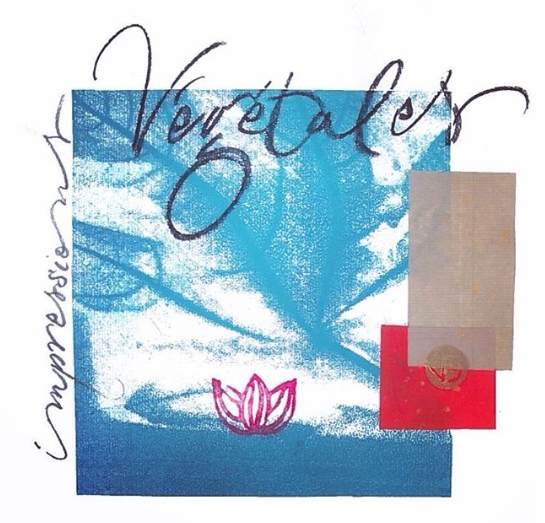
Vous pouvez découvrir d’autres travaux réalisés avec cette même technique chez Quintessence_aqualetters, ou Lettres Vagabondes et bien sûr dans le portfolio de celle qui nous a tout appris, Marine !